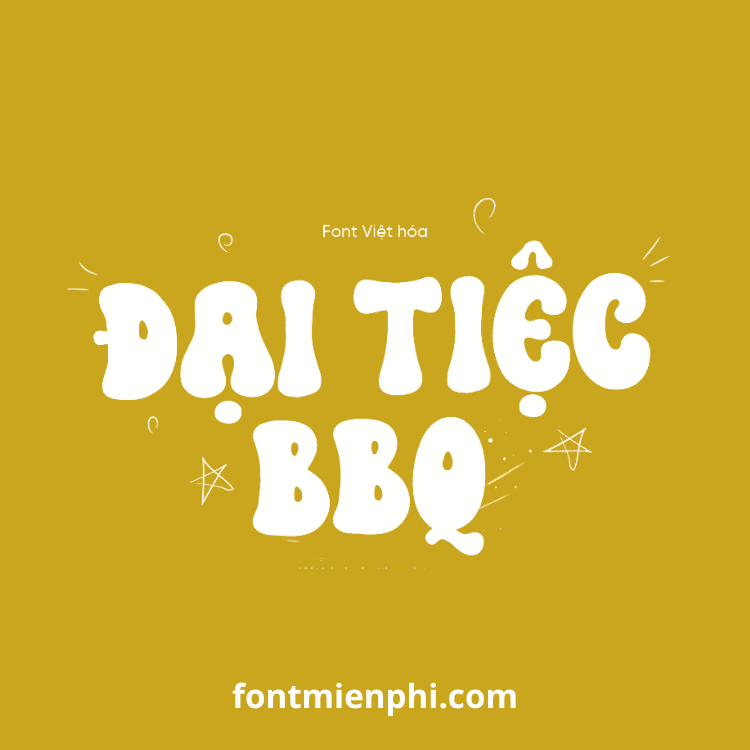
Font Việt hóa 1FTV VIP Forever Dreaming
Font Việt Hóa 1FTV VIP Forever Dreaming – Nét Chữ Mộng Mơ Đầy Cảm Xúc
Giới thiệu nổi bật:
1FTV VIP Forever Dreaming là font chữ nghệ thuật việt hóa cao cấp với những nét uốn lượn mềm mại tựa như giấc mơ tuổi trẻ. Font chữ này được giới designer đặc biệt yêu thích nhờ vẻ đẹp lãng mạn, phù hợp cho các thiết kế hướng đến phái nữ và những thông điệp ngọt ngào.
Đặc điểm ấn tượng:
• ✨ Kiểu chữ thanh thoát với các nét cong mềm mại kết hợp họa tiết hoa lá tinh tế
• ✅ Bộ ký tự tiếng Việt đầy đủ chuẩn Unicode, hỗ trợ mọi bảng mã thông dụng
•  Phong cách vintage nhẹ nhàng phù hợp thiết kế thiệp cưới, lời chúc, nhãn hàng mỹ phẩm
Ứng dụng sáng tạo:
• Thiết kế thiệp mời, card visit sang trọng
• Làm poster, banner sự kiện đám cưới
• Thiết kế bao bì mỹ phẩm, nước hoa
• Các dự án cần phong cách nữ tính, lãng mạn